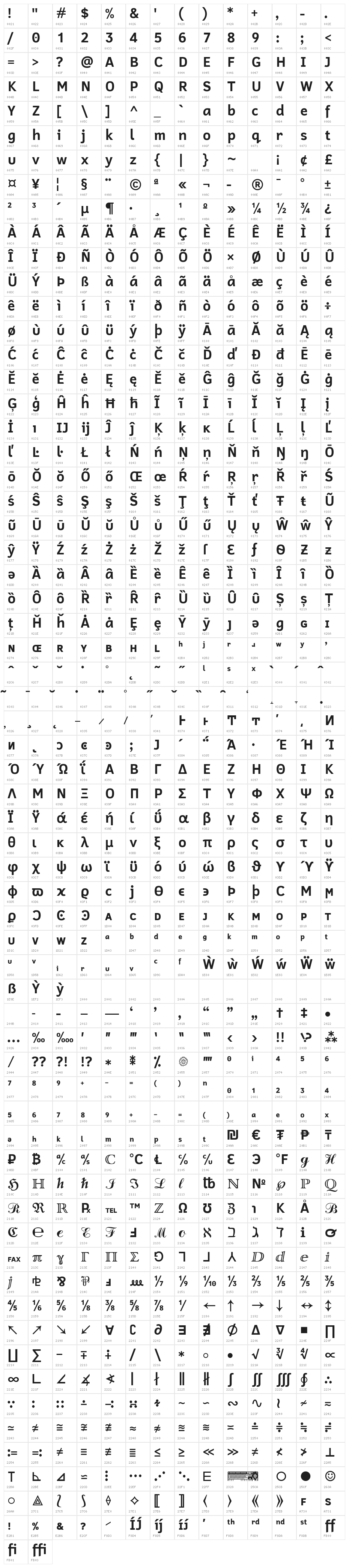
Cadman Bold Font
| Progetti proposti | Ideal for branding, headlines, posters, and digital content where clarity and impact are essential. |
Cadman Bold